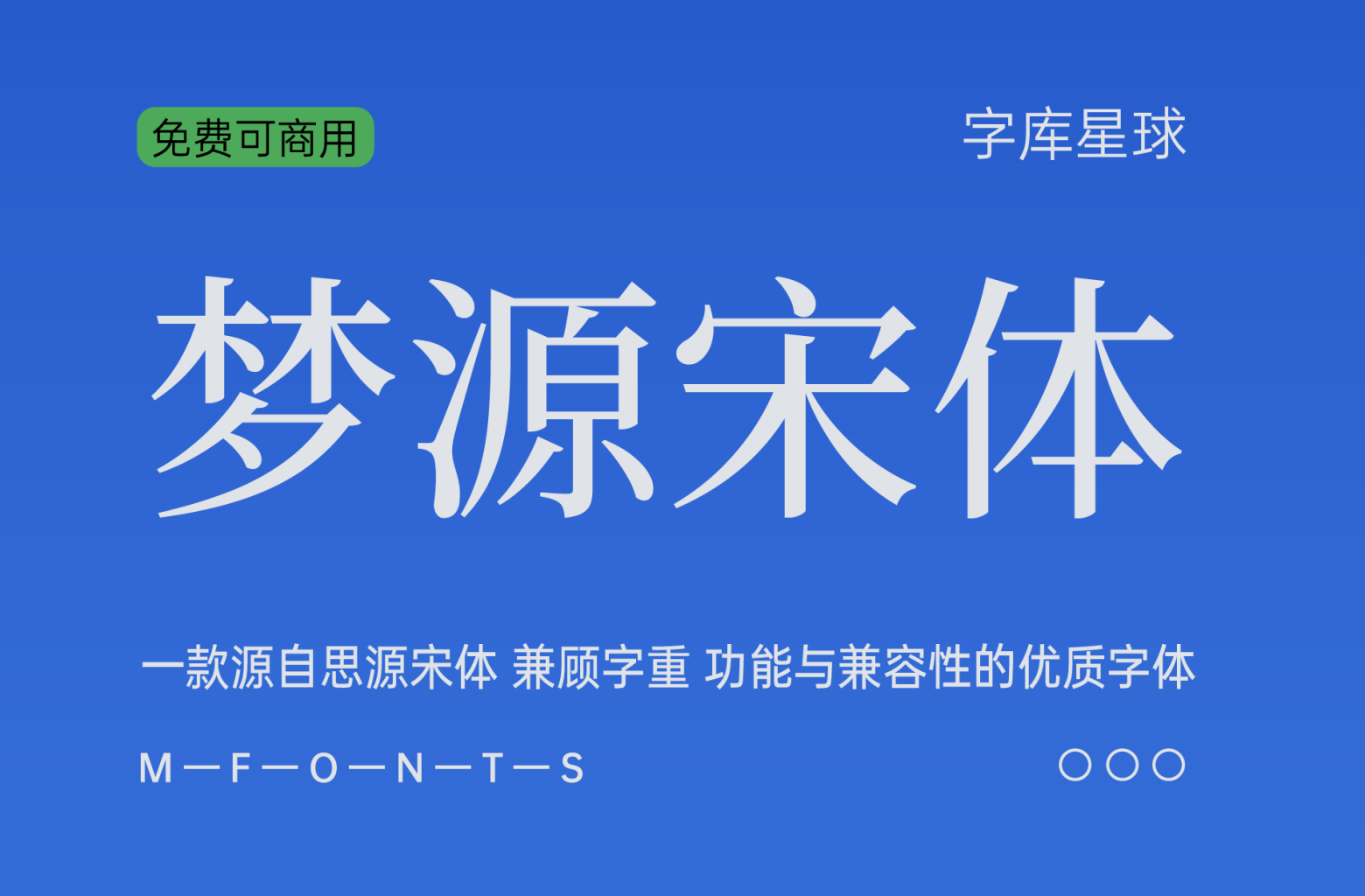
梦源宋体是一款源自思源宋体,兼顾字重,功能与兼容性的优质免费可商用字体。
梦源宋体是源自思源宋体多语言字体家族,兼顾字重、功能与兼容性,货真价实的27字重!做设计起飞的赶脚!免费商用!绝非什么小作坊的描边加粗!
梦源字体系列是可变版思源字体使精细的字重调节成为了可能。然而,可变字体因轮廓重叠、渲染故障、软件兼容性等原因给实际使用造成了阻碍。本项目将可变版思源字体的大量中间字重实例化为传统单字重字体,合并了重叠的曲线轮廓,在保证最大兼容性的前提下,提供更加细腻、丰富的字重选择。此外,本项目修复了思源系列广泛存在的 Adobe 行高过大问题。本系列字体的其他功能(如字形、竖排、kerning、多语言、异体字、曲线精度等)与思源系列保持完全一致,未做任何修改。
梦源字体以可变版思源黑体和思源宋体为母版,对其字重轴 wght
进行插值运算,提取中间字重。插值算法经过了如下考量:
- 暴露给最终用户的
wght
轴经 Adobe 添加的avar
表人工干预,导致字重随wght
非线性增大(参见 issue #6)。插值算法需排除avar
表的干扰; - 加粗时,黑体和宋体的黑度变化不同:黑体的横竖笔画同时变粗,而宋体只有竖笔画变粗,因此在人眼看来,黑体的加粗速度要高于宋体,且其细体字重比粗体对粗度的变化更为敏感。简单的线性插值适用于宋体,但如果直接用在黑体上,就会导致细体字重被粗体“挤压”。
插值算法
- 绕开思源可变源文件中的
avar
表,确保插值算法不受人工预设值干扰; - 梦源宋体采用线性插值(linear interpolation):从最细端 250 开始,粗度每步增加常数 25 ,直到最粗端 900,得到 250-275-300-…900 共计 27 字重;
- 梦源黑体采用二次多项式插值(quadratic interpolation):从最细端 250 开始,粗度每步增加 19.4 + f ^ 2;其中,系数 f 的起始值为 1,每一步增大 0.1;以此类推,直到最粗端 900,得到 250-270.4-291.01-…-900 共计 27 字重。
因为插值算法绕过了思源可变内置的 avar
表,所以本项目采用的 wght
值与思源可变字体没有任何关联,也没有与思源在数值上完美对应的字重。在实际使用中,可对比思源字体找出梦源字体最接近的字重。